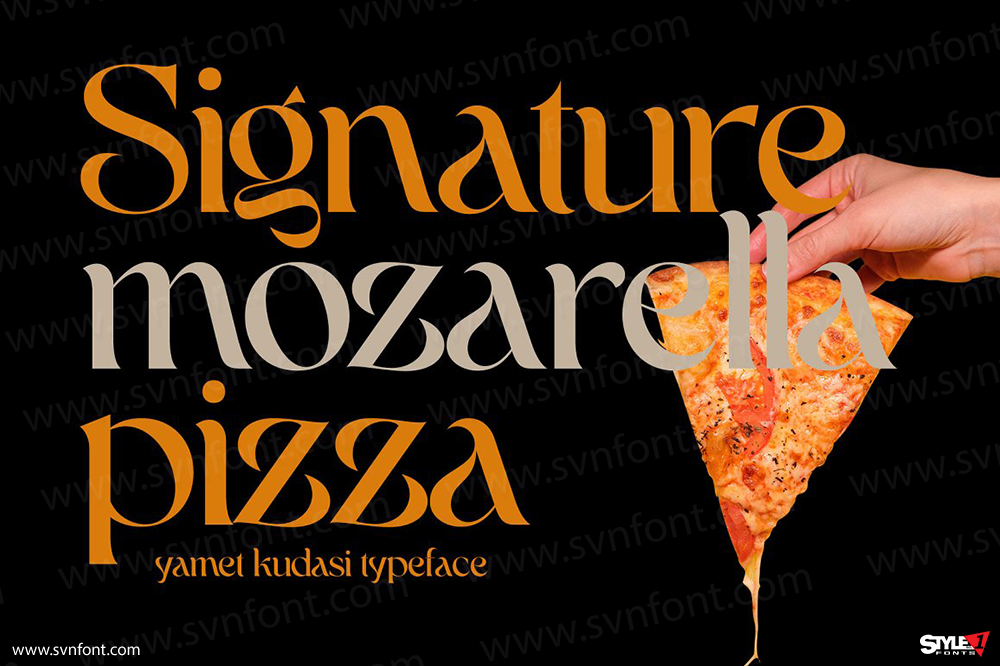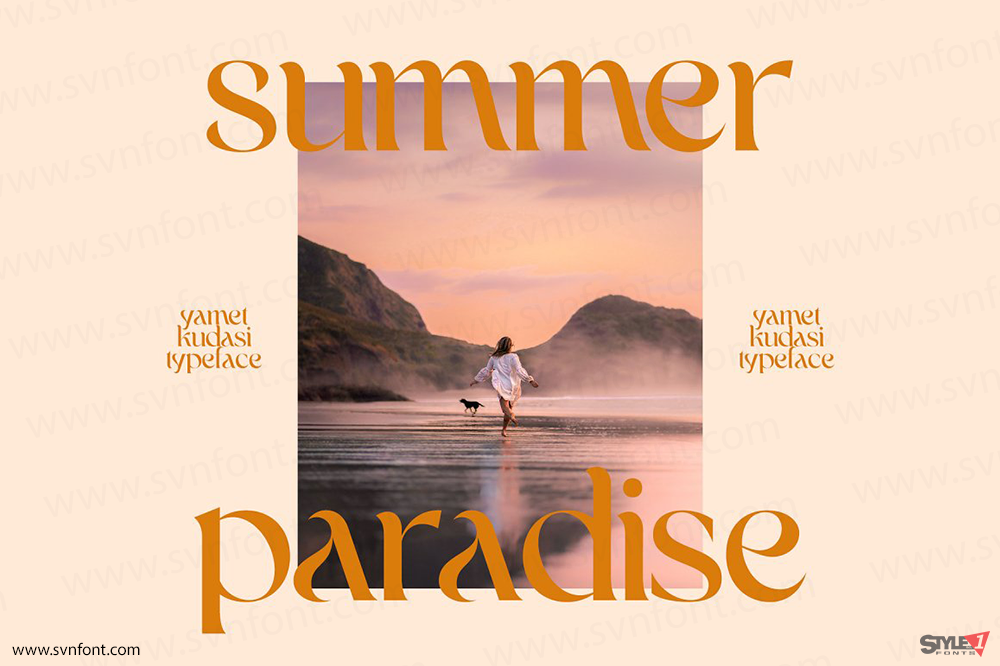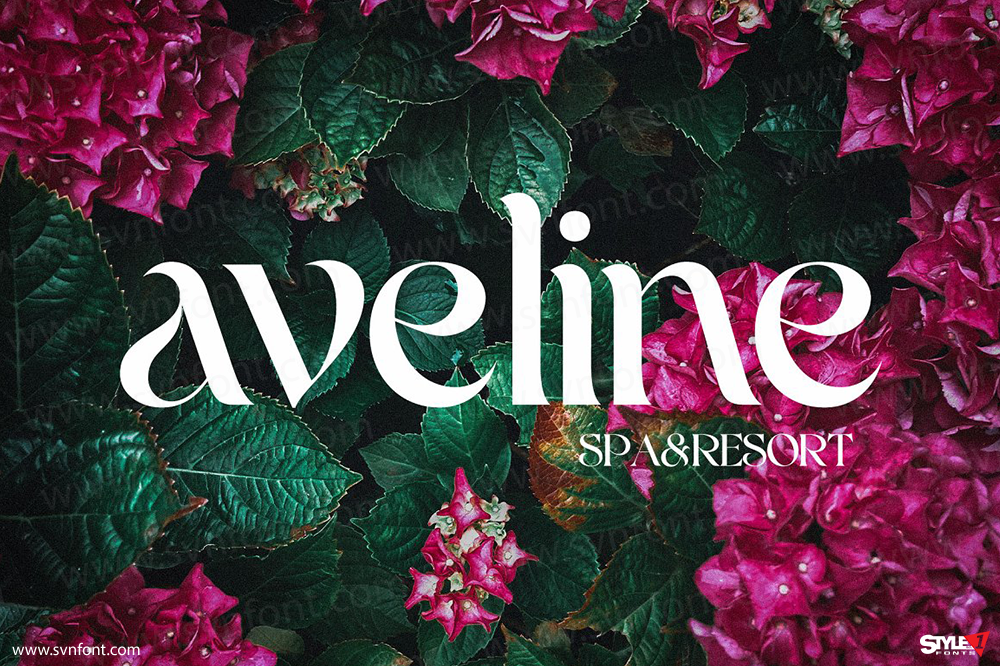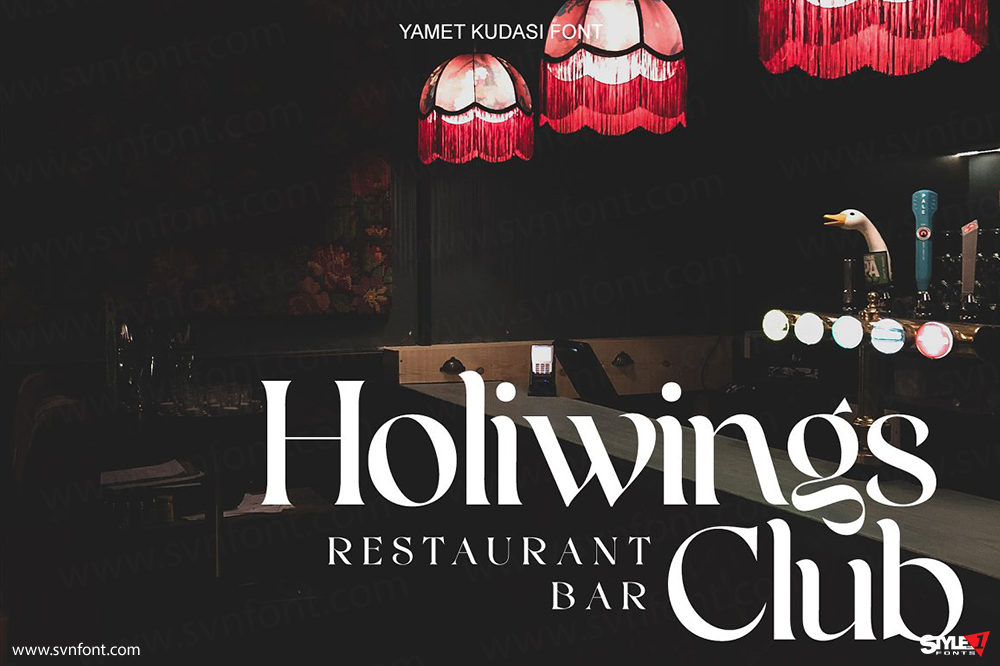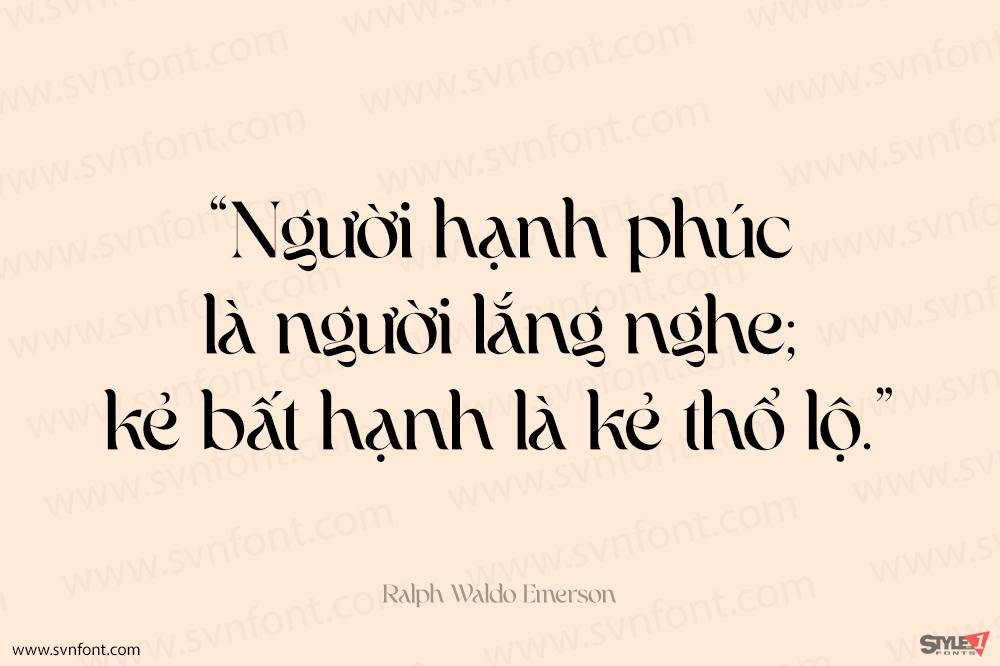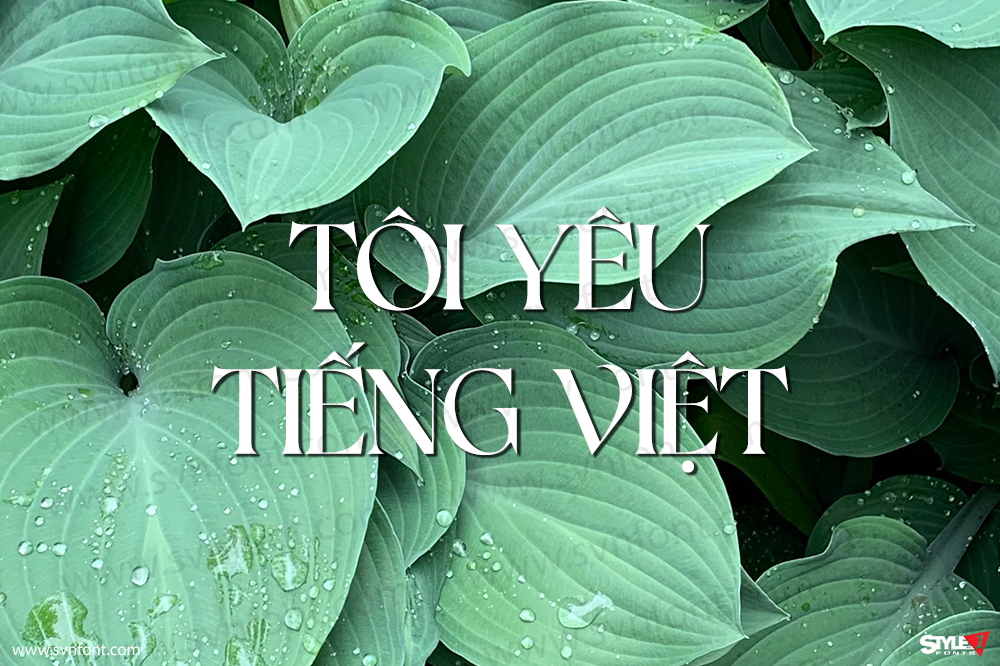
Yamet Kudasi là một font mang phong cách retro–modern độc đáo, được chế tác với độ chính xác cao trong từng chi tiết. Font rất phù hợp cho thiết kế branding, logo, thiệp chúc mừng, tiêu đề, bao bì và nhiều ứng dụng sáng tạo khác.
Nhà thiết kế: Dean Nugraha
Nhà phát hành: Dean Nugraha